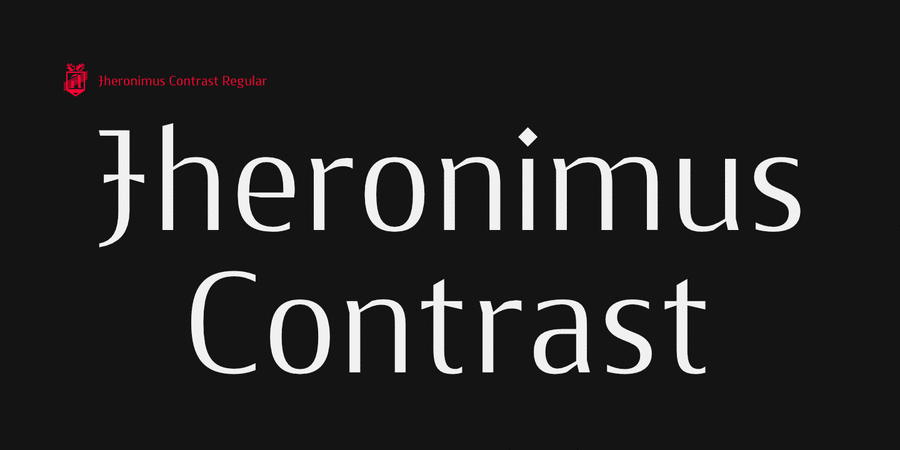
Jheronimus – це нео-гуманістичний ґротеск з варіативною насиченістю і контрастом. Він має відкриту апертуру, прямі зрізи й помірну висоту рядкових знаків. Шрифт має єдиний впорядкований ритм знаків, тому він добре читається на екрані в дрібному кеглі. У нього узгоджені пропорції літер, округлі елементи у формі стиснутого овалу, чітко виражені з'єднання й декоративні знаки пунктуації. Jheronimus задовольнить вимогливого друкаря. Також він має мінускульним цифри в кращих традиціях гуманізму.
У Jheronimus м'який, впізнаваний характер у поєднанні з чіткими формами. Це створює гостре, кристальне враження. Він підходить для дизайну амбітних, темпераментних текстів. Шрифт схожий за стилістикою на картини данського художника Ієроніма Босха. Його ім'я було взято в якості назви. Шрифт розробив Олексій Поповцев у 2019 році.
Асоціації з сімейством шрифтів JheronimusОсобистість і характер гарнітури:
твердий, оригінальний, характерний, гострий, різкий, чіткий, серйозний, жорсткий, залізний, сталевий, міський, стійкий, незвичайний, гордий, сучасний, динамічний, артистичний, дорогий, технічний, карбований, авторитетний, переконливий, важливий, монументальний, архітектурний, впевнений, екстравагантний, рівний, амбітний, експериментальний, суворий, героїчний, лицарський, сміливий, благородний, красивий, виразний, майстерний, легендарний, художній, аристократичний, старовинний, історичний, джентльменський, пивний, пафосний, освічений, елітний, якісний, гуманітарний, срібний, культурний, естетичний, розкішний, дорогоцінний, унікальний, добірний, багатий, дзвінкий, важкий, сильний, яскравий, помітний, активний, крихкий, прозорий, скляний, сріблястий, золотий, витончений, вишуканий, біблійний, християнський, церковний, релігійний, сакральний, худий, кам'яний
Місто, мода, одяг, розкіш, гроші, інструмент, пам'ятник, меморіал, архітектура, дизайн, Трофей, нагорода, геральдика, музей, надгробок, скульптура, історія, ресторан, лицар, обладунки, тату, татуювання, меч, антикваріат, пиво, паб, бібліотека, мистецтво, література, проза, музика, вино, срібло, живопис, художник, коньяк, преміум, шоколад, прикраса, ювелір, коштовності, сервіровка, віскі, годинник, меню, взуття, театр, замок, туризм, банкнота, золото, монета, бутік, Біблія, вечір, захід сонця, пейзаж, шолом, люкс, прапор, армія, граніт Гарнітура має ознаки стилів:
— Гарнітура асоціюється з віком: